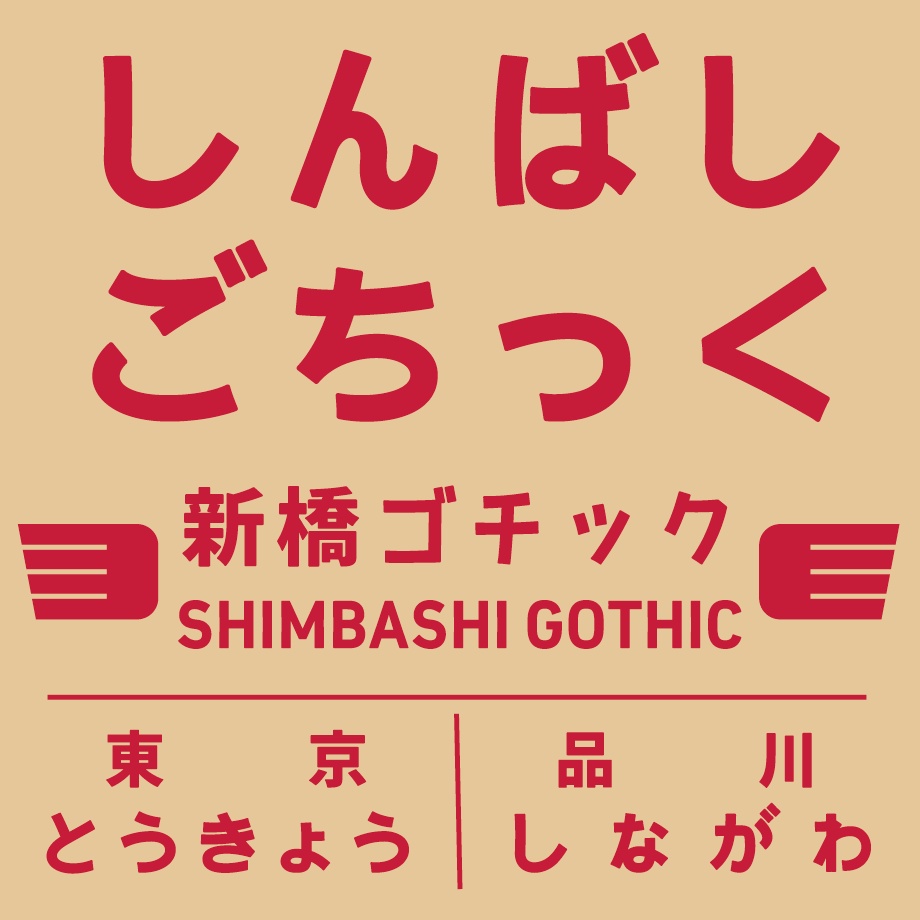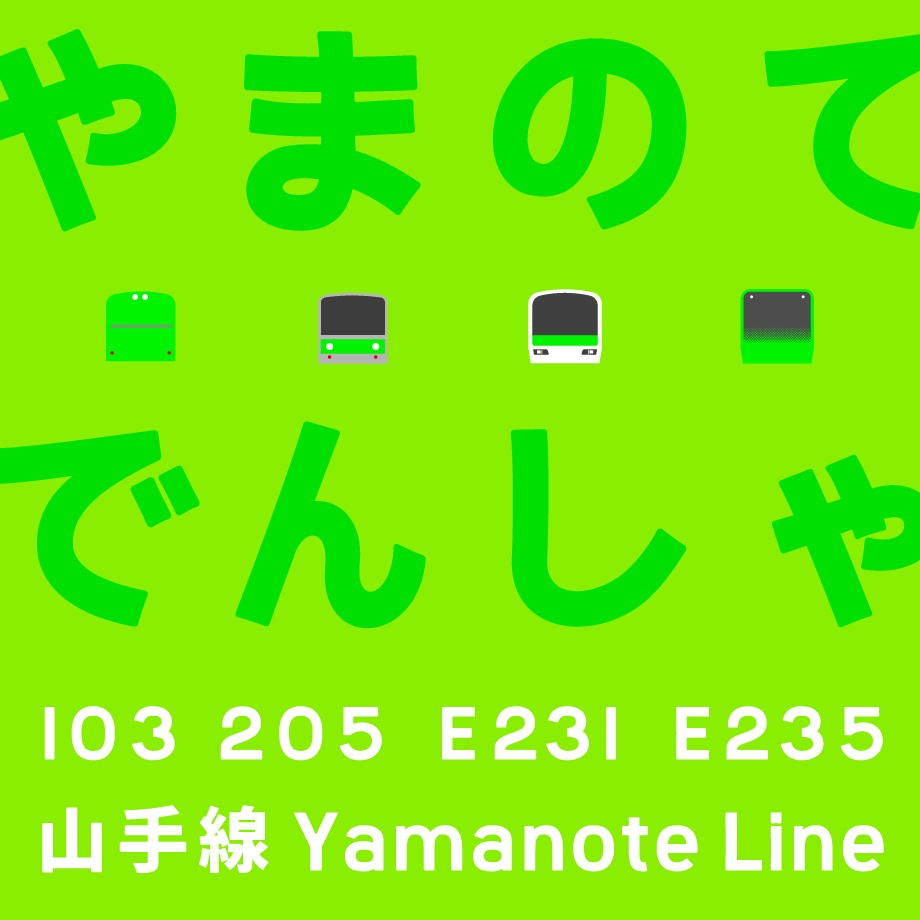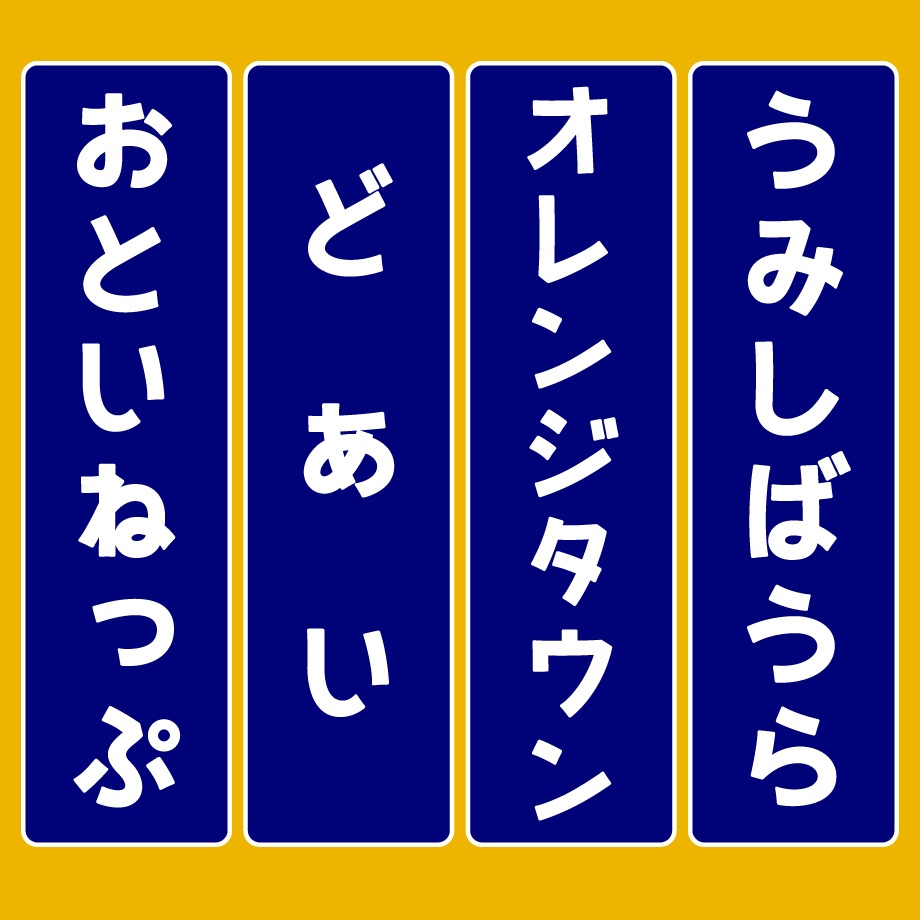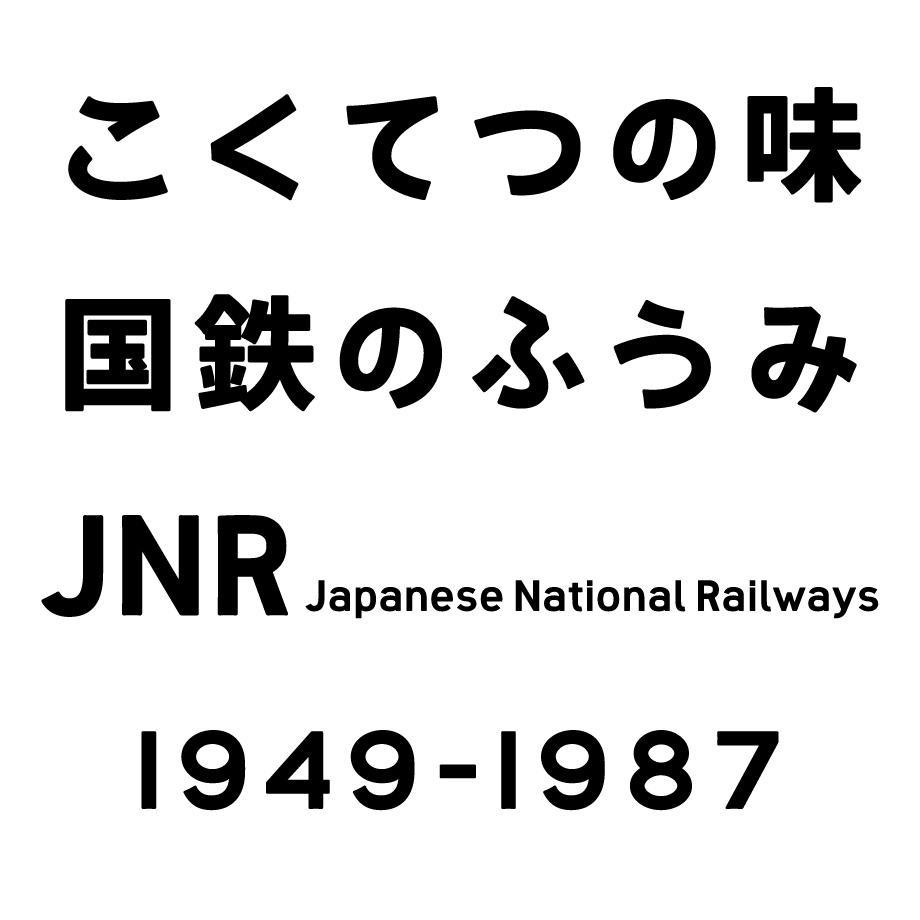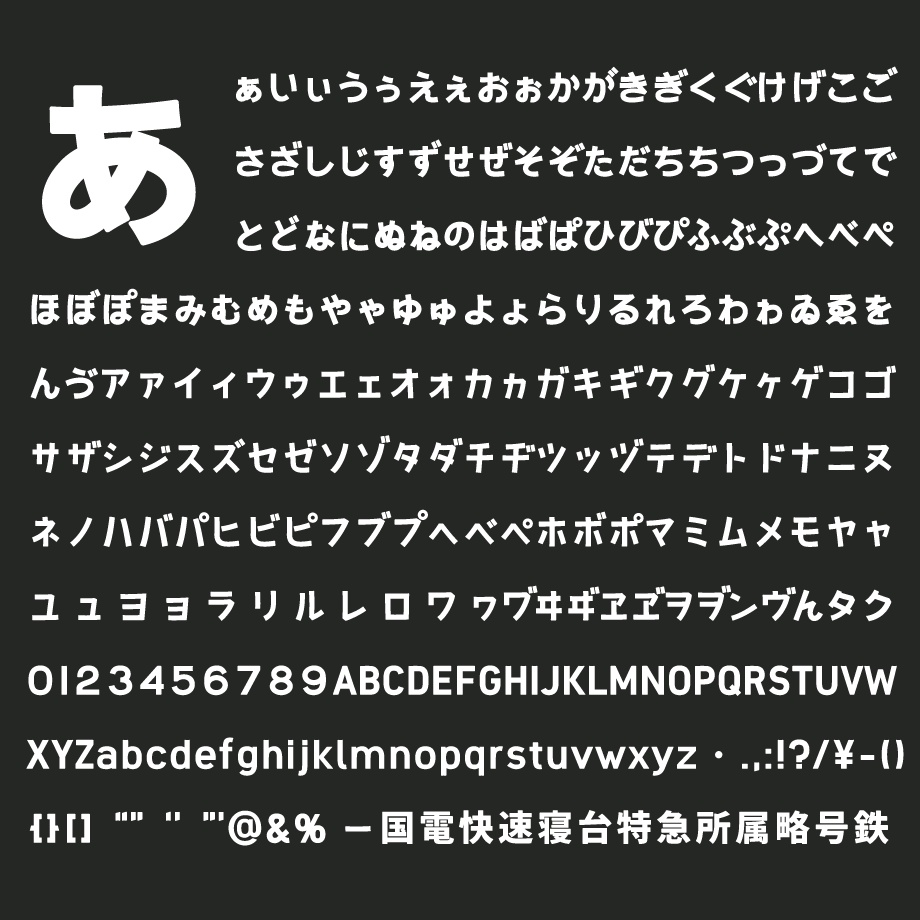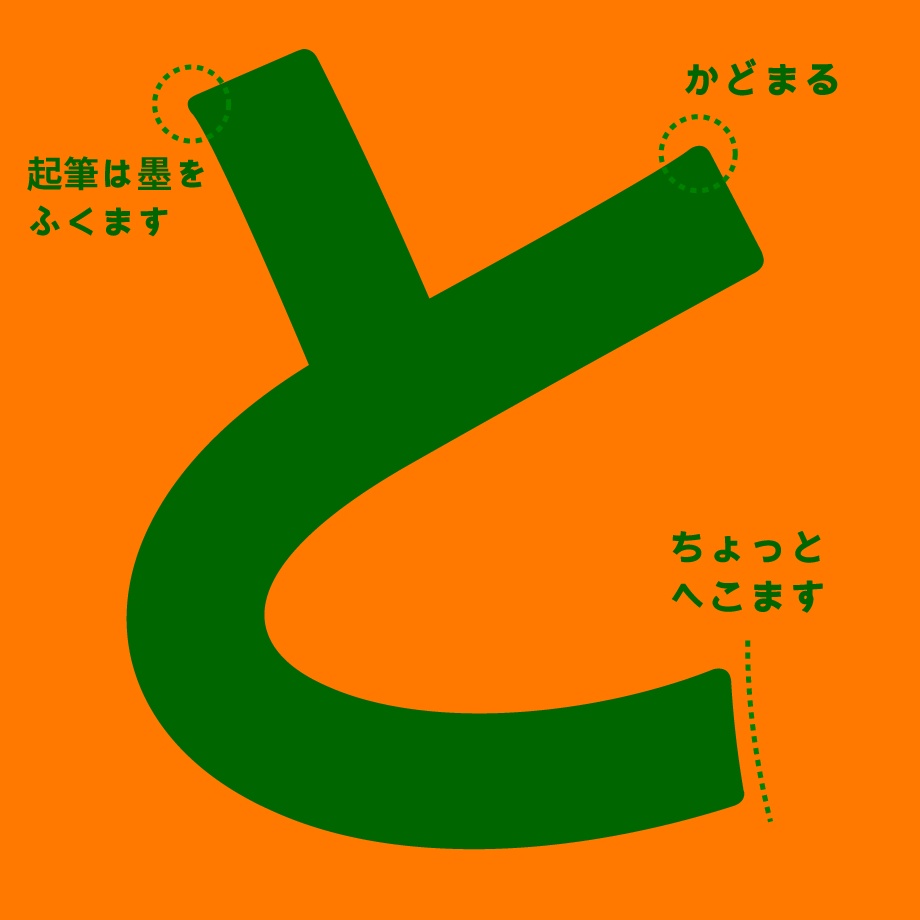
日本語フォント「しんばしごちっく」
日本語(和文)フォント「しんばしごちっく」 ● このフォントについて しんばしごちっく は、フリーのOpenTypeフォントである「源ノ角ゴシック(Source Han Sans)」の日本語漢字部分の角を丸める加工を行った派生フォントです。 ひらがな、カタカナ、英数字、一部記号は Typingart & Co. が制作したグリフです。 収録文字はひらがな、カタカナ、英数字、一部記号、漢字(教育、常用、JIS第一、第二水準)です。 ● ライセンスと著作権について ・フォントデータに含まれる、源ノ角ゴシック由来の文字グリフの著作権は Adobe が所有しています。 ・源ノ角ゴシックと同じ SIL Open Font License 1.1 のもとで使用することができます。 SIL Open Font License 1.1 の内容は、アーカイブに同梱の SIL_Open_Font_License_1.1.txt に記載されています。 日本語訳は、以下から参照することができます。 https://licenses.opensource.jp/OFL-1.1/OFL-1.1.html ● 頒布元 しんばしごちっくの最新版は、以下のサイトで頒布しています。 https://typingart.booth.pm ● 改変元 源ノ角ゴシック (Source Hans Sans) https://fonts.adobe.com/fonts/source-han-sans-japanese